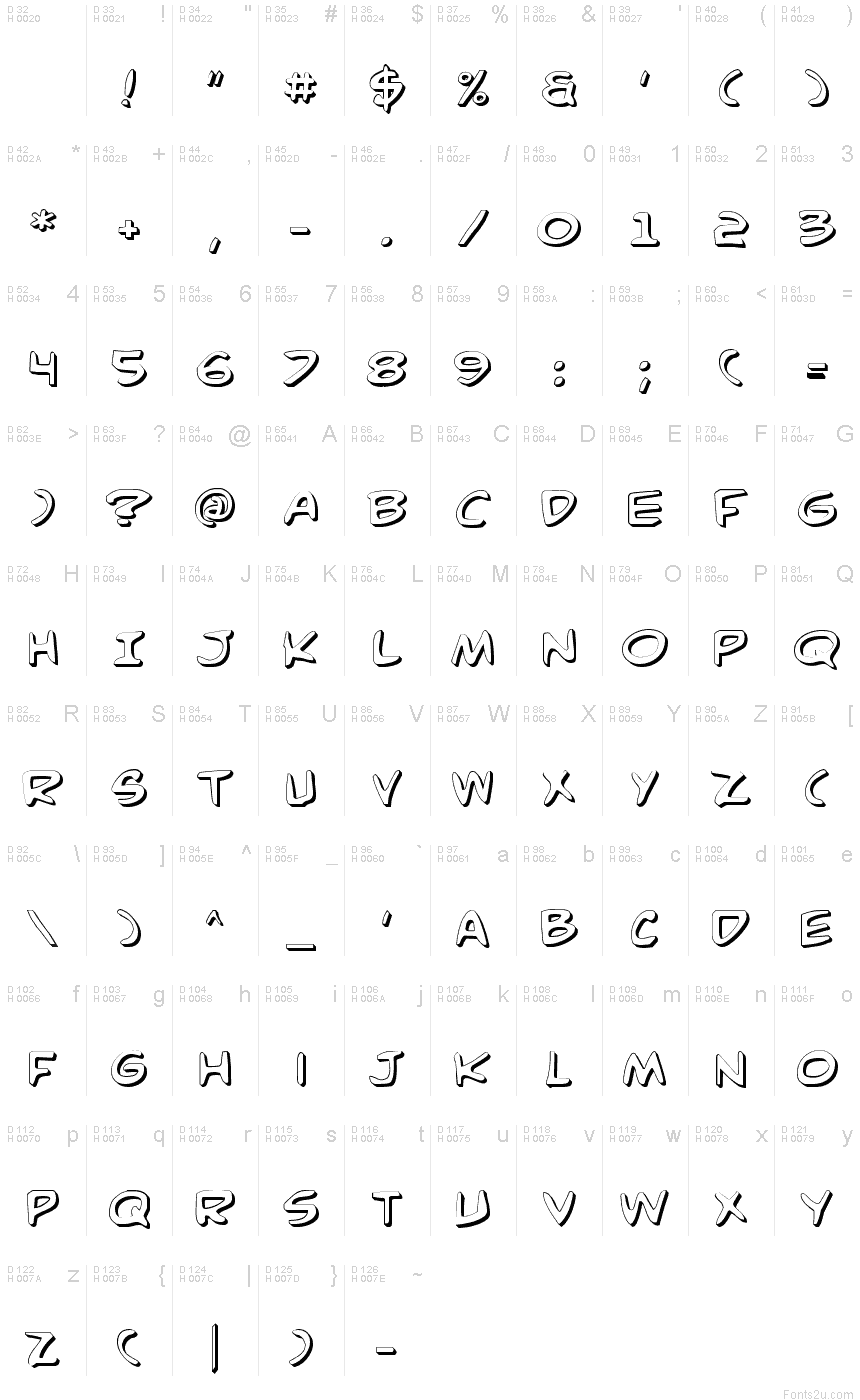
Comic Book Commando 3D od Iconian Fonts to darmowy, komiksowy font typu display, który dosłownie wyskakuje ze strony. Dzięki lekkim konturom i masywnemu cieniowi 3D nadaje każdemu słowu energię sobotnich poranków: jest wyrazisty, dynamiczny i nieco zawadiacki, ale przy tym pozostaje czytelny.
Comic Book Commando 3D świetnie sprawdzi się na okładkach komiksów, logotypach superbohaterów, nakładkach do gier, opakowaniach zabawek, zaproszeniach na przyjęcia dla dzieci, naklejkach i miniaturach na YouTube. Używaj dużego rozmiaru, aby zachować ostrość wewnętrznych białych przestrzeni, i dodaj jasne wypełnienie lub teksturę półtonową dla uzyskania komiksowej dynamiki. Dla dłuższych tekstów lub podpisów połącz ten darmowy font z prostym krojem bezszeryfowym.